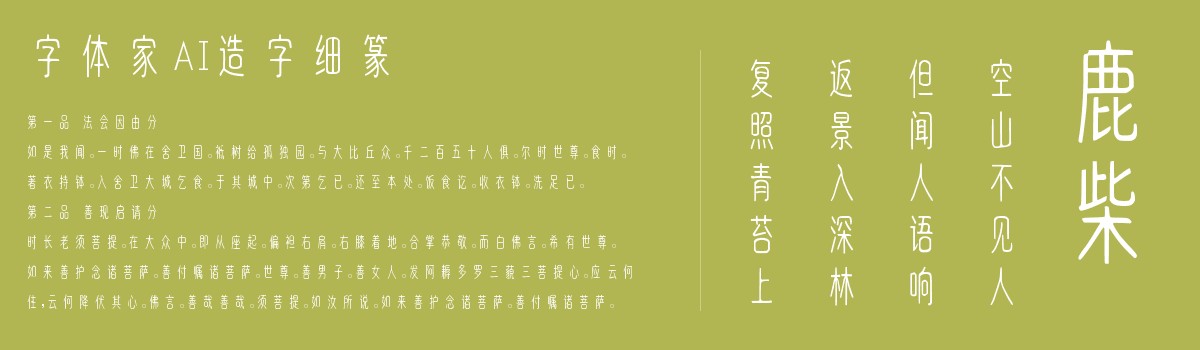
字体家AI造字细篆
字体家AI造字细篆是一款由字体家AI神笔造字生成的艺术字体,这款细篆字体,笔画如蚕丝般纤细却暗藏韧性,线条圆润流畅,转折处无棱角,似水流淌般自然过渡。结构对称均衡,纵向舒展,各部分比例协调如古典梁柱般端正。整体气质典雅沉静,细而不弱,透着书卷的精致与古韵,仿佛能触到墨迹在宣纸上轻柔游走的温润感。。适合用于一些广告标题、平面文案、海报标题、网页广告用字的编辑。